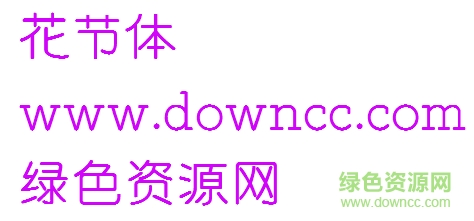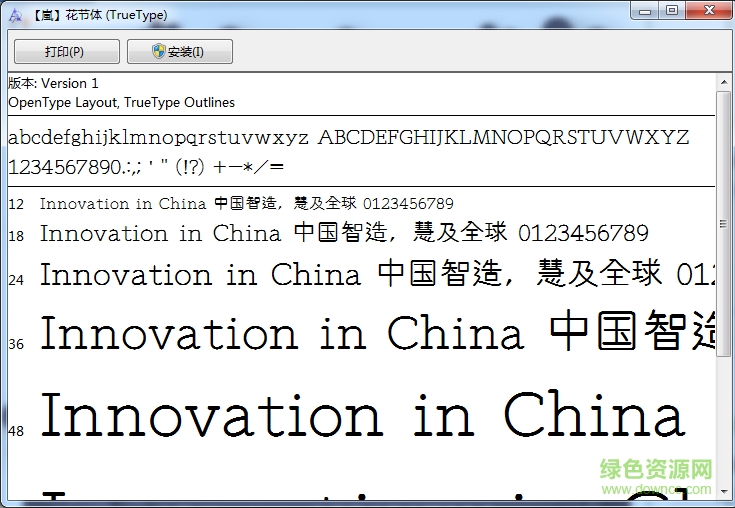
花節(jié)體ttf是一款字跡清秀、風(fēng)格靚麗的時尚藝術(shù)字體,有著婉約和端正之美,讓你的閱讀更加舒適,讓你的文字書寫別具美感,喜歡的朋友來綠色資源網(wǎng)即可免費體驗哦!
花節(jié)體整體偏柔和溫潤,如花般的優(yōu)雅和美好,字體干凈不拖沓,很有端莊秀麗之風(fēng),讓人頗為眼前一亮!可廣泛適用于海豹世紀(jì)、名片設(shè)計、藝術(shù)設(shè)計等多種場合!